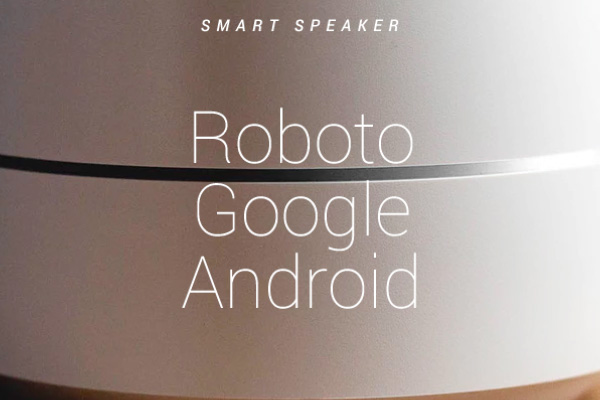
6 款适合科技行业的字体分享,科技行业设计师必藏
在科技行业里,每天要处理无数产品页面、用户界面、文档和营销材料。字体选择不当,页面看起来会显得凌乱、阅读费力,或者专业感不足。适合科技行业的字体能让界面干净清爽、让用户快速理解内容、让整体品牌显得现代又可靠。
下面我按照不同场景和风格,给你推荐几款我实际用过的字体,帮助你快速找到最匹配的。
现代简洁:Inter 字体
适合网页UI和SaaS产品
Inter是我最推荐的现代简洁字体之一。它是完全免费的开源字体,设计时专门考虑了屏幕显示,字母形状友好、圆润却不柔和,整体给人一种干净利落的感觉。相比老的Arial,Inter的字重变化更多(从极细到黑体),在小字号时也不容易糊在一起。
低对比度、几何元素多、屏幕优先设计、支持多语言包括中文、英文、日文等。笔画干净,数字和标点也清晰。
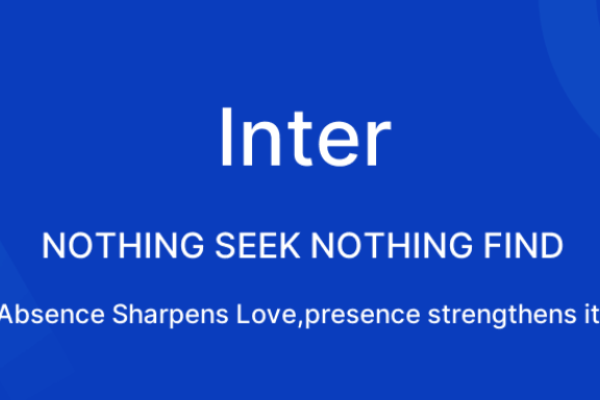
可靠中性:思源黑体
适合中文网站和企业产品
思源黑体是Google与Adobe联合开发的开源字体,我现在几乎所有中文字体项目都从它开始。它覆盖简体中文、繁体中文、英文等多种语言,笔画平衡,现代又不失传统美。
无衬线黑体、笔画清晰、字重多(7种加可变版)、对屏幕和打印都友好、支持多种语言字符。设计时注重可读性,数字和标点也处理得很专业。
友好科技:Roboto
Roboto是Google Fonts里的经典,它的外形更圆润友好,笔画柔和却有科技感。我经常用它做App图标和启动画面。
用Roboto时,我发现界面按钮和文字过渡更自然。用户反馈“看起来好用”“不陌生”。缺点是相比Inter,它在小字体时略微柔和一点,如果需要极致清晰,可能需要调整权重。
DIN:适合硬件和企业级产品
DIN是德国风格的字体,我在一些工业科技产品上用过。它更硬核,适合强调“科技精确”。
风格特点:几何无衬线、数字清晰、年轻却稳重、笔画锐利。
适用场景:硬件产品说明书、工业仪表界面、车企或硬件科技APP。
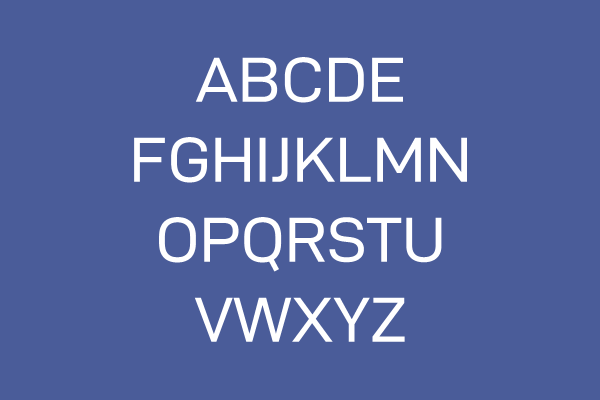
优雅现代:Helvetica Now
Helvetica的现代版,我在一些企业级科技项目中试过。它经典却有更新。经典无衬线、优雅稳重、适合标题。适用高端产品介绍、公司介绍页。
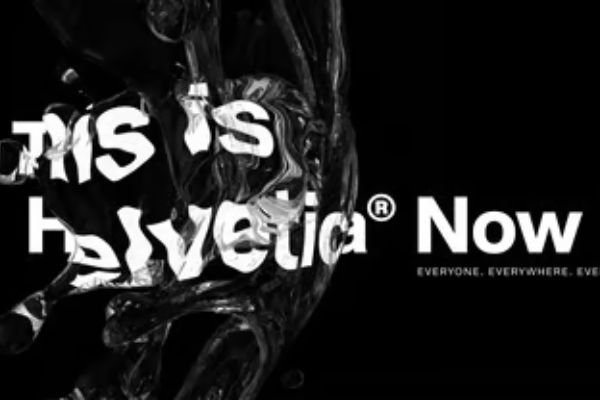
手写活泼:Poppins字体
Poppins是一个手写风字体,我觉得它给科技产品加点亲和力。圆润手写感、易读、颜色丰富。适用教育科技、消费级科技App的活动页面。